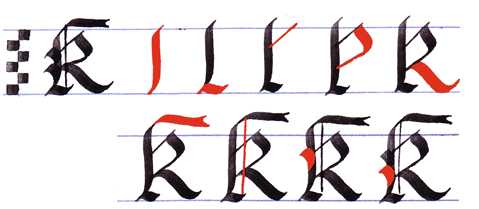
Готическое письмо — Википедия
Материал из Википедии — свободной энциклопедии
Текущая версия страницы пока не проверялась опытными участниками и может значительно отличаться от версии, проверенной 29 декабря 2016; проверки требуют 11 правок. Текущая версия страницы пока не проверялась опытными участниками и может значительно отличаться от версии, проверенной 29 декабря 2016; проверки требуют 11 правок. Латинская Библия (1407, Англия)
Страница нидерландско-немецкого словаря (1759). Нидерландский текст набран антиквой, а немецкий — готическим шрифтом- О письме готского языка см. готское письмо
Готи́ческое письмо́ — семейство почерков латинского письма эпохи Средневековья. Было распространено в ряде европейских стран с середины XII до XVII века.
С началом книгопечатания появились наборные готические шрифты — знаменитая Библия Гутенберга была набрана вариантом текстуры. В Италии первые печатные книги с готическим шрифтом появились в 1473 году (это были сочинения
Готический шрифт. Пошаговые уроки. Прописные буквы
Это завершающий урок серии пошаговых уроков по готическому шрифту. Если вы овладели строчными буквами из предыдущих уроков, то научиться писать прописные будет довольно просто.
Удобно, что все буквы готического алфавита строятся из одинаковых элементов. Изучив одну букву вам будет легче писать остальные.
Полезная информация о прописных буквах готического шрифта
В готике есть много разновидностей прописных букв. Смотрите больше примеров, отмечайте и запоминайте особенности. Создайте свою коллекцию прописных букв. После того, как изучите основы, вы сможете комбинировать и импровизировать с различными элементами, адаптируя их под конкретный проект.
Как правило прописные буквы значительно выступают за пределы строки вверх и вниз, в отличие от строчных. Они занимают квадратную область или даже широкий прямоугольник, а формы их довольно округлые.
Прописные в готическом шрифте так сильно отличаются от строчных, по крайней мере, по двум причинам. Скорее всего они произошли из букв унциального письма и позднего верасльского, которые имеют округлые формы. И конечно, в традиционном письме они облегчали поиск новой строки среди монотонных вертикальных штрихов.
Вторая причина объясняет почему готические прописные так хорошо смотрятся в традиционных цветах: алом, синем или зеленом. Для выделения особо важных абзацев вокруг прописной буквы рисуют золотые рамки или замысловатые узоры. Готическая письменность вообще располагает к экспериментам в прописных буквах, так что, я надеюсь, вы будете получать большое удовольствие от них.
Хорошо, давайте перейдем к практике.
Готическое письмо: прописные готические буквы от A до Z.
Наши заглавные буквы имеют высоту шесть ширин пера. Это значит, что если вы пишете пером, шириной 3 мм, то высота буквы будет 18 мм. Чтобы создать нужную сетку для упражнений удобно воспользоваться одним из генераторов сеток, про которые я написал здесь.
Дальше будут инструкции выполнения буквы по штрихам. Каждый новый штрих обозначен красным цветом. Тонкие штрихи рисуются левым уголком кончика пера. Вы просто поворачиваете ручку пера против часовой стрелки и проводите линию левым уголком пера. Так мы уже писали в третьем уроке по строчным буквам.
Вот пример:
Основным правилом готического письма является то, что мы всегда ведем пером сверху вниз, либо слева на право. В любом случае перо всегда должно двигаться назад, оставляя за собой штрих. Если вести пером вперед, то оно будет цепляться за бумагу, издавай жуткий скрежет и оставляя неровный штрих.
Изучение буквы «A», как ни странно, не поможет в изучении остальных букв. Зато, она довольно простая. Здесь приведен довольно нежный вариант буквы. Попробуйте вариацию с одинаковыми ножками. Просто нарисуйте нижнюю ножку правого штриха также плоско, как и первого.
На самом деле, в готическом письме есть много вариаций прописных букв, так что когда освоите эту форму – экспериментируйте.
В этом примере буквы «B» есть прекрасный образец украшения готического письма — это шипы с левой стороны первого вертикального штриха (5 и 6 позиция в последовательности). Я надеюсь, что вы будете часто использовать это украшение в своих буквах. Эти шипы могут иметь разную форму — прямую или изогнутую. Пишите ту, которая вам сейчас больше нравится.
Как нарисовать такой шип: поставьте перо под углом 45º так, чтобы оно слегка касалось первого вертикального штриха буквы и начинайте вести ручку вправо и сразу вниз, образуя таким образом запятую. Угол пера должен быть всё время 45º. Следите за тем, чтобы нижний кончик этой запятой не выглядывал за границы вертикального штриха.